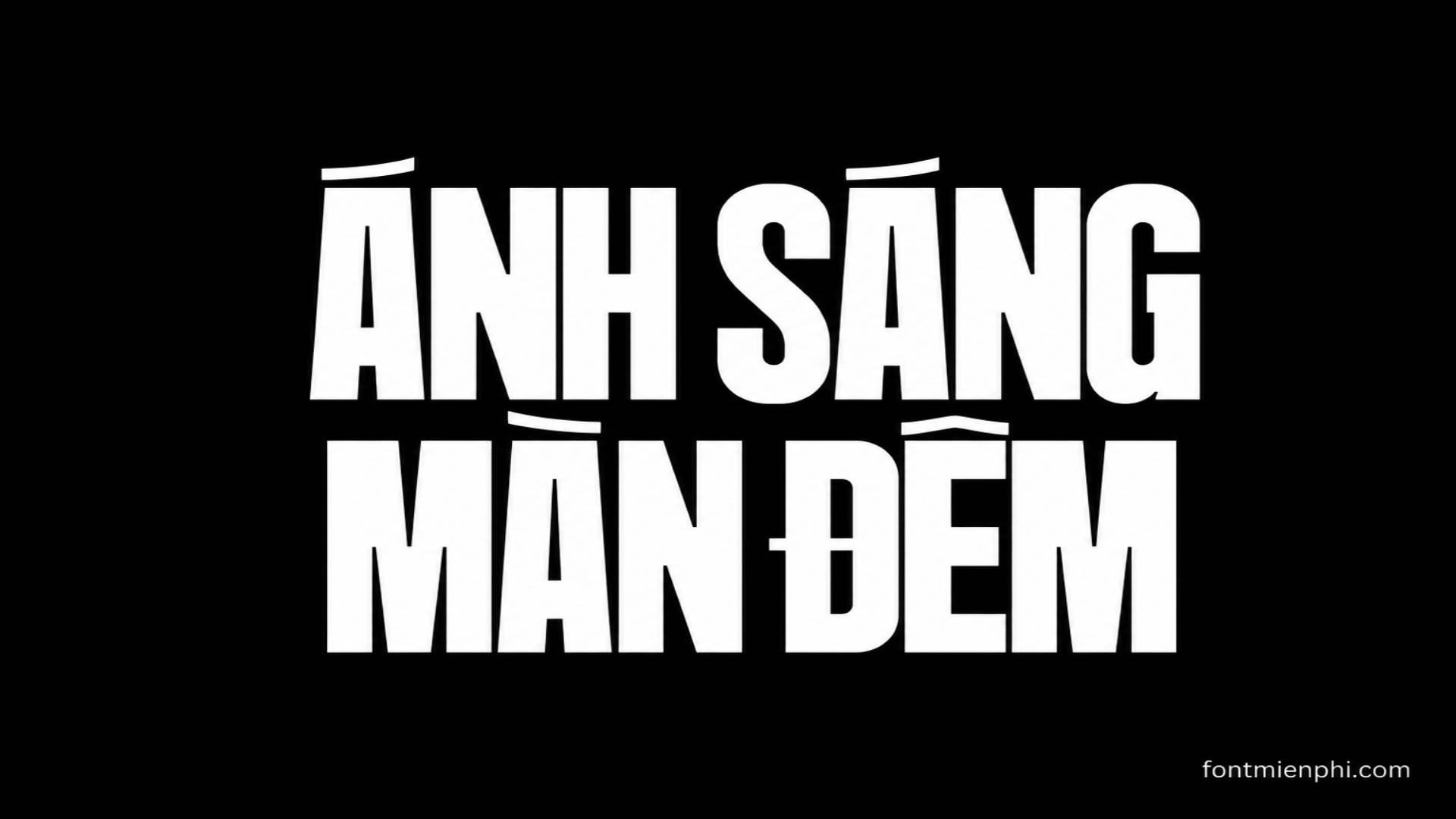
Nếu bạn đang tìm kiếm một phông chữ mang lại sức nặng thị giác “khủng”, có khả năng lấp đầy không gian thiết kế và thu hút sự chú ý ngay từ cái nhìn đầu tiên, thì Font Việt hóa PS BIGGER chính là mảnh ghép bạn không thể bỏ lỡ. Đúng như tên gọi “BIGGER”, phông chữ này sinh ra để làm những điều to lớn, táo bạo và phá cách nhất.
1. Tổng quan về Font PS BIGGER
PS BIGGER là một phông chữ thuộc dòng Display Sans-serif (không chân, chuyên hiển thị tiêu đề). Đặc trưng cốt lõi của phông chữ này nằm ở trọng lượng chữ cực kỳ lớn (Ultra Bold/Black) và form dáng vuông vức, mập mạp. Nó mang lại một cảm giác vô cùng vững chãi, hiện đại và mang đậm hơi thở của nghệ thuật đường phố (Street-art) hoặc thiết kế Brutalism (chủ nghĩa thô mộc).
Khi sử dụng các font chữ quá béo, người dùng thường e ngại việc các dấu câu tiếng Việt sẽ bị dính vào nhau hoặc làm hỏng cấu trúc chữ. Tuy nhiên, phiên bản PS BIGGER Việt hóa đã được xử lý vô cùng khéo léo. Các dấu thanh (sắc, huyền, hỏi, ngã, nặng) và dấu mũ (ă, â, ê, ô, ơ, ư) được căn chỉnh tỷ lệ vàng, đảm bảo chữ vẫn to, dày nhưng cực kỳ rõ ràng và dễ đọc.
2. Đặc điểm nổi bật của Font PS BIGGER Việt Hóa
Với ngoại hình đồ sộ, PS BIGGER sở hữu những ưu điểm “độc nhất vô nhị” mà hiếm phông chữ nào có được:
• Tối đa hóa sức mạnh thị giác (Maximum Impact): Độ dày cực đại của các nét chữ giúp thông điệp của bạn “đập” ngay vào mắt người xem, lấn át mọi yếu tố phụ trợ xung quanh.
• Phong cách cá tính, nổi loạn: Mang đến năng lượng bùng nổ, trẻ trung, rất phù hợp với nhóm khách hàng Gen Z.
• Kerning hoàn hảo cho chữ “béo”: Đội ngũ Việt hóa đã tính toán tỉ mỉ khoảng cách giữa các ký tự, giúp chữ không bị đan xen hay tạo ra những khoảng trắng (white space) vô lý khi gõ.
• Ứng dụng linh hoạt các hiệu ứng: Nhờ diện tích mặt chữ lớn, PS BIGGER là “mảnh đất màu mỡ” để bạn chèn các hiệu ứng Texture (độ nhám), Gradient (chuyển màu), hoặc lồng ghép hình ảnh (Clipping Mask) vào trong chữ.
3. Ứng dụng thực tế của Font PS BIGGER trong thiết kế
Vì là một phông chữ mang tính chất giật gân và gây chú ý mạnh, PS BIGGER tỏa sáng nhất khi được đặt ở vị trí trung tâm:
Mẹo phối Font (Typography Tip): Tuyệt đối không dùng PS BIGGER cho các đoạn văn bản dài vì nó sẽ tạo thành một khối đen đặc làm người xem nhức mắt. Hãy dùng nó cho từ khóa chính, tiêu đề ngắn (1-4 từ) và kết hợp với một font chữ mảnh, đơn giản (như Roboto Light, Montserrat Thin) để tạo sự tương phản tối đa.
• Thiết kế Thời trang & Local Brand: Là lựa chọn hoàn hảo để làm Typography in trên áo thun (T-shirt), Hoodie, áo khoác mang phong cách Streetwear, Hiphop.
• Banner Khuyến mãi & Flash Sale: Cực kỳ hiệu quả khi dùng để viết các từ khóa như “BIG SALE”, “GIẢM SỐC”, “50% OFF” trên các sàn thương mại điện tử.
• Thumbnail YouTube & Social Media: Giúp tiêu đề video nổi bật chói lòa giữa bảng tin, kích thích tối đa sự tò mò và tỷ lệ click (CTR).
• Poster Sự kiện & Âm nhạc: Thể hiện tinh thần bùng nổ của các đêm nhạc EDM, Rap, Hip-hop hoặc các giải đấu Thể thao điện tử (Esports).